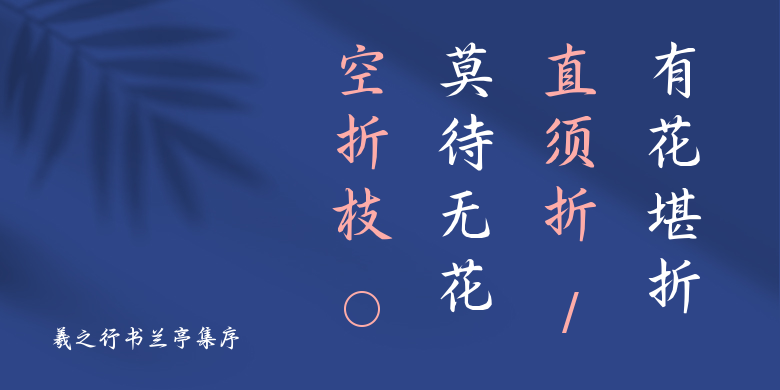
羲之行书兰亭集序
羲之行书兰亭集序,这款字体结构工整、笔画清晰,兼顾美观与易读性,适用于标题、正文、海报、包装、LOGO 等多种场景。字形优雅稳定,风格百搭耐看,适配日常排版与创意设计,让文字呈现更舒适、更具质感。羲之行书兰亭集序一笔一画,皆是细节,以均衡的比例、流畅的线条打造舒适视觉体验,字形端正大气,风格简约现代。无论是商业设计、品牌宣传还是日常排版,都能轻松驾驭,让文字更有格调与力量。羲之行书兰亭集序字体下载。